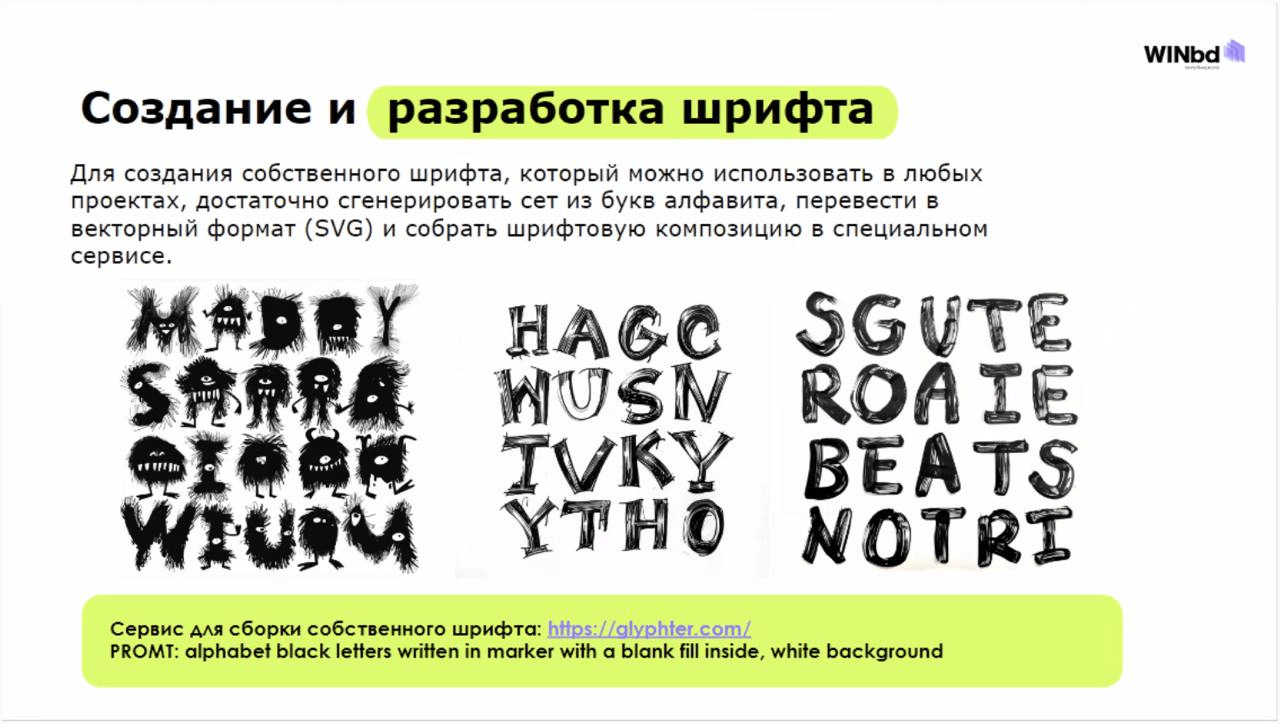
Зачем выбирать стандартные шрифты, когда можно создать свой?
Уникальные буквы в вашем стиле, от каллиграфии до фантазийных образов, легко собрать с помощью нейросетей.
Как это сделать
1) Начнем с Midjourney. В начале нужно описать, что именно вы хотите получить: букву или целый набор букв, их стиль и особенности написания. Например, «Буква А, пышная, с элементами ручной графики, мягкие линии».
Пример промта: alphabet black letters written in marker with a blank fill inside, white background
2) Доработка деталей. Если не хватает каких-то букв или элементы не соответствуют ожиданиям, их можно доработать вручную — удалить ненужное или дополнить недостающее. Это как с паттернами: редактируйте, чтобы добиться идеального результата.
3) Применение. Такие шрифты отлично подходят для брендинга, творческих и коммерческих проектов. А главное — процесс создания не требует профессиональных навыков дизайнера.
Попробуйте сами! Нейросети упрощают даже то, что раньше казалось сложным.